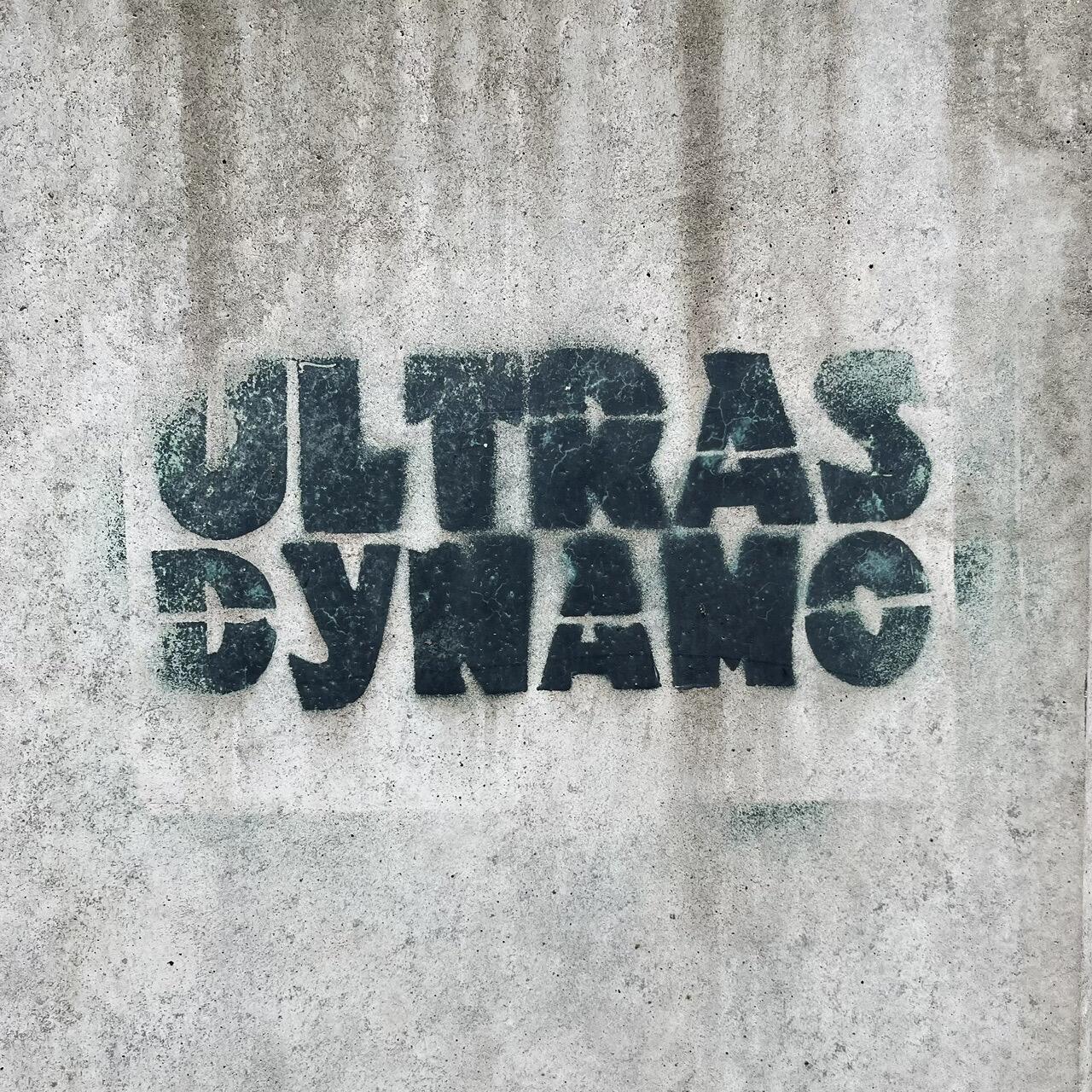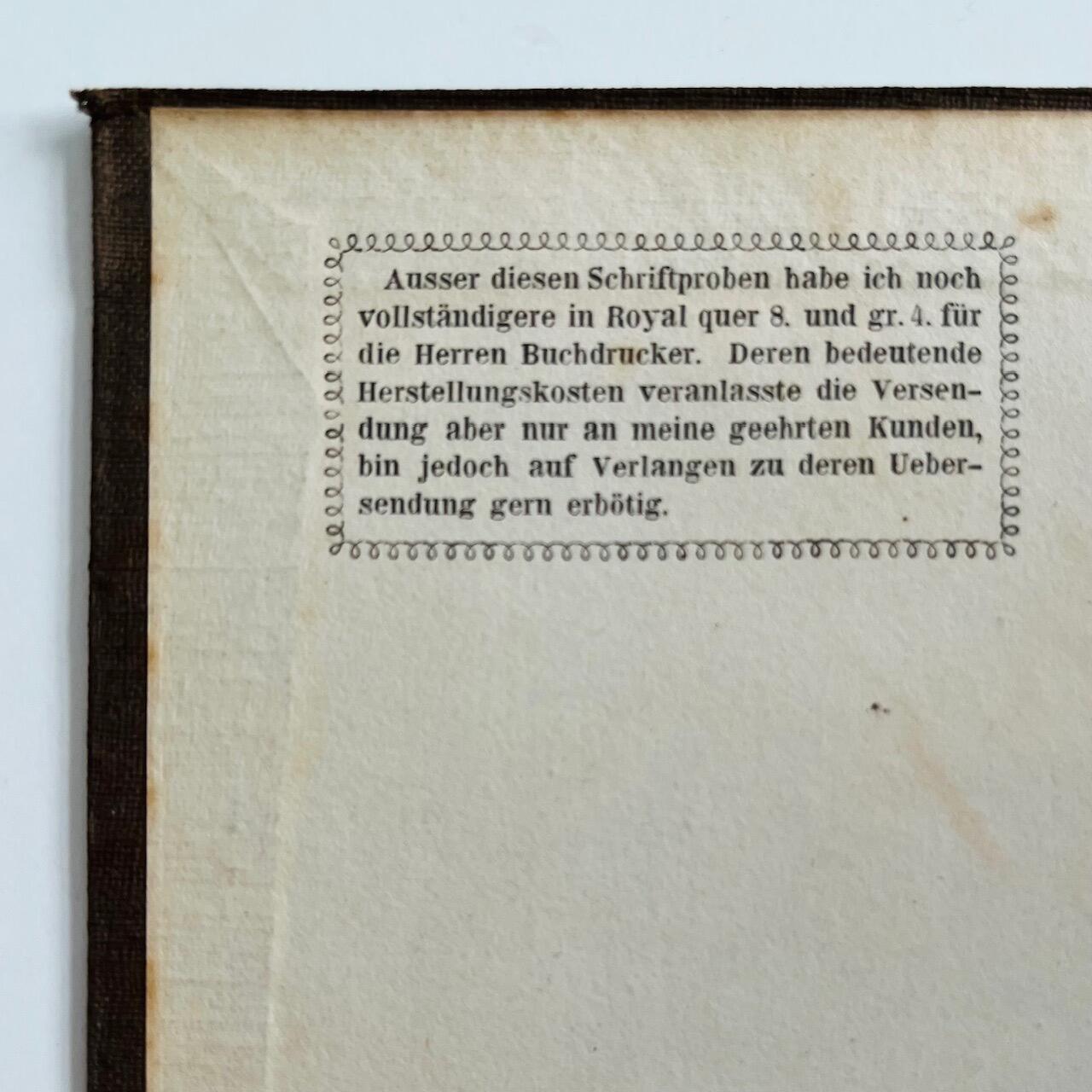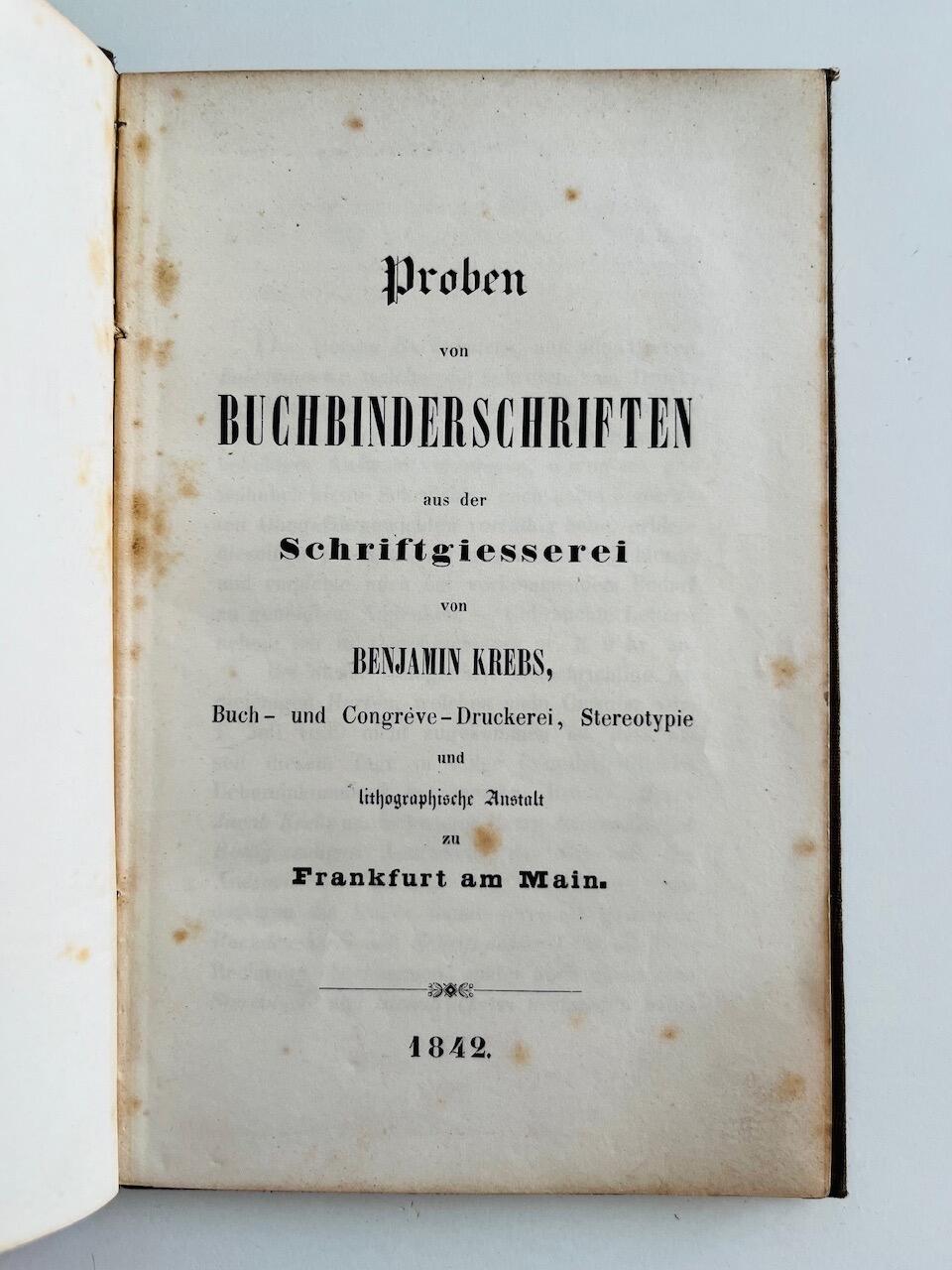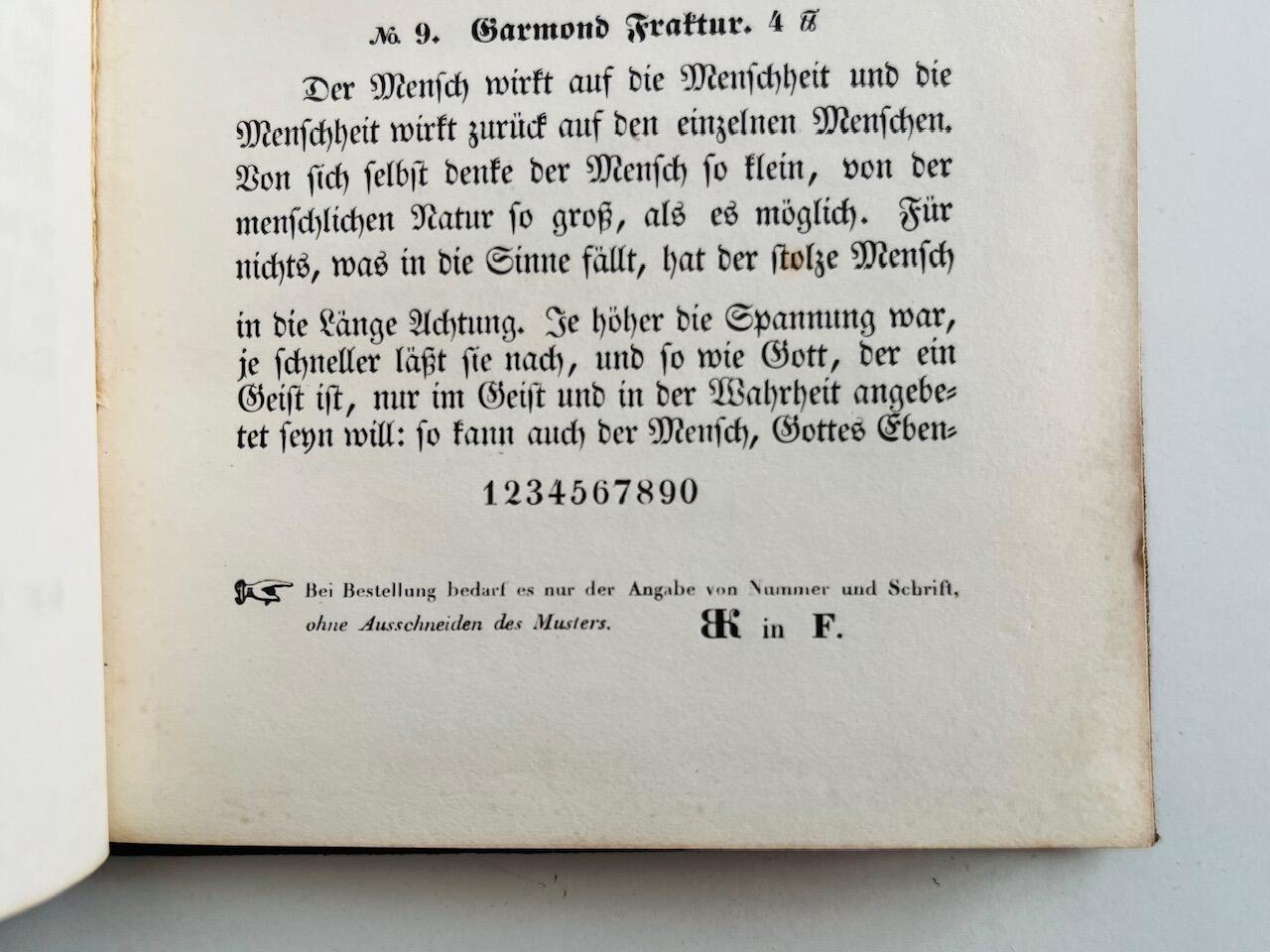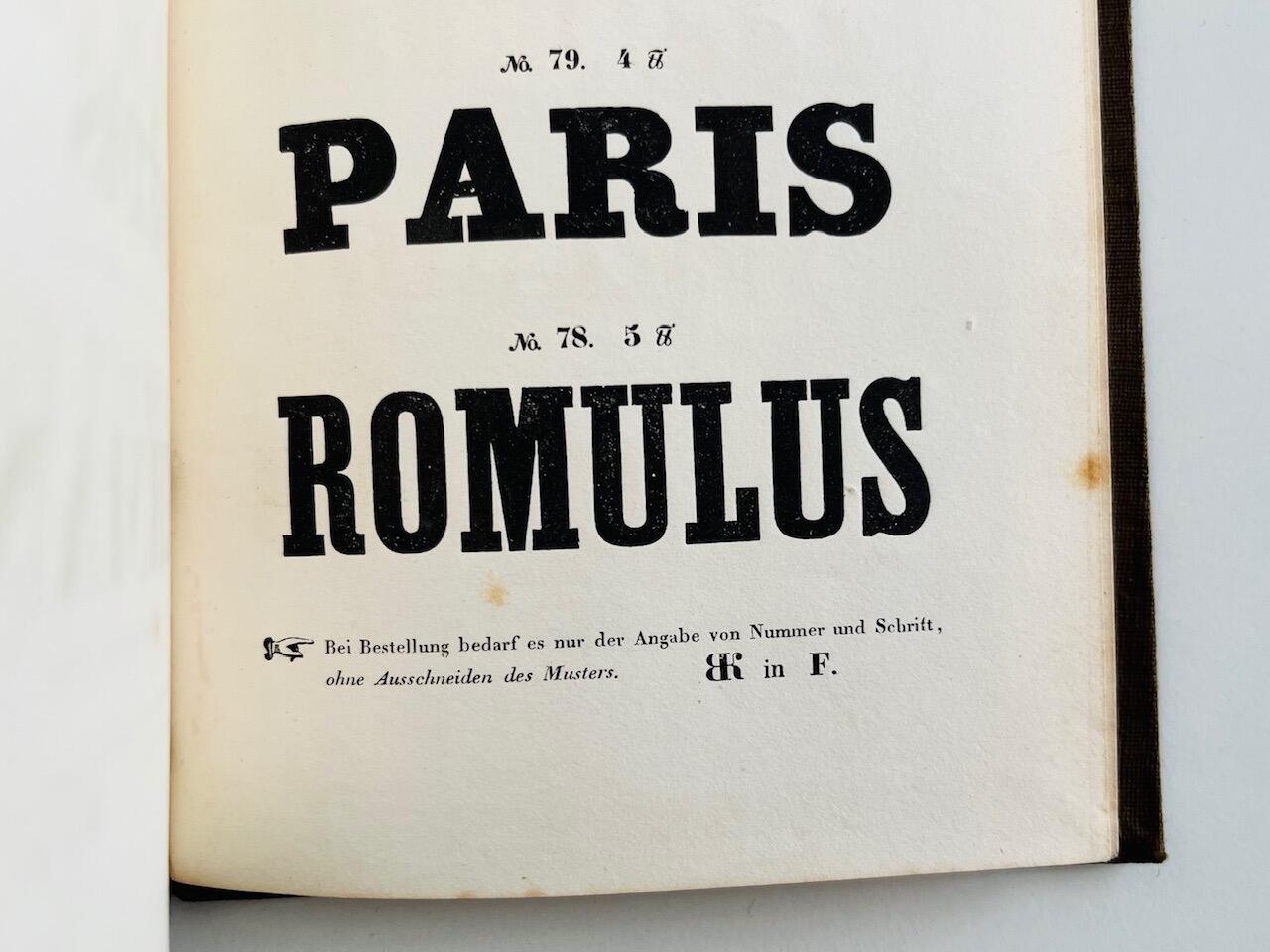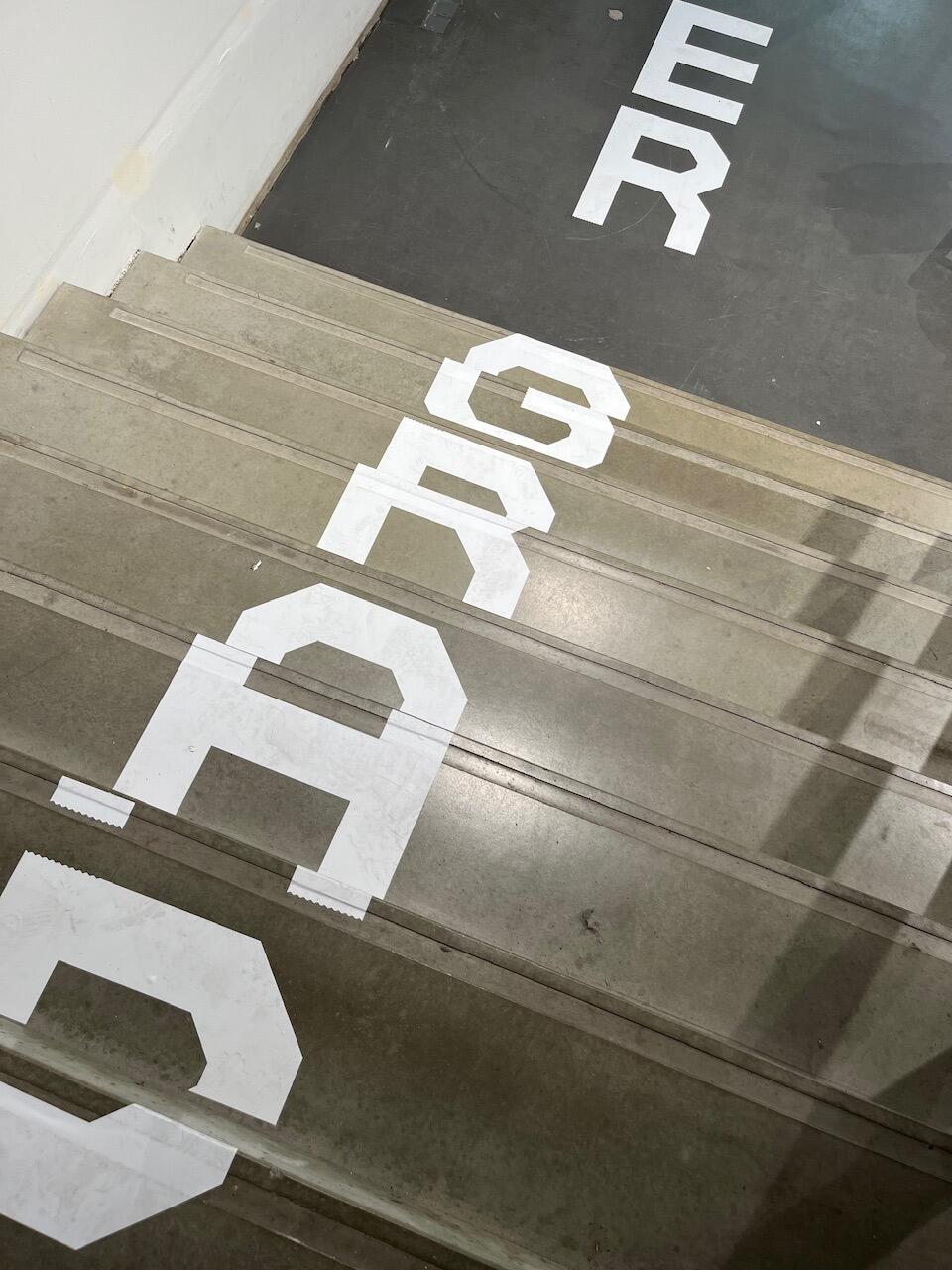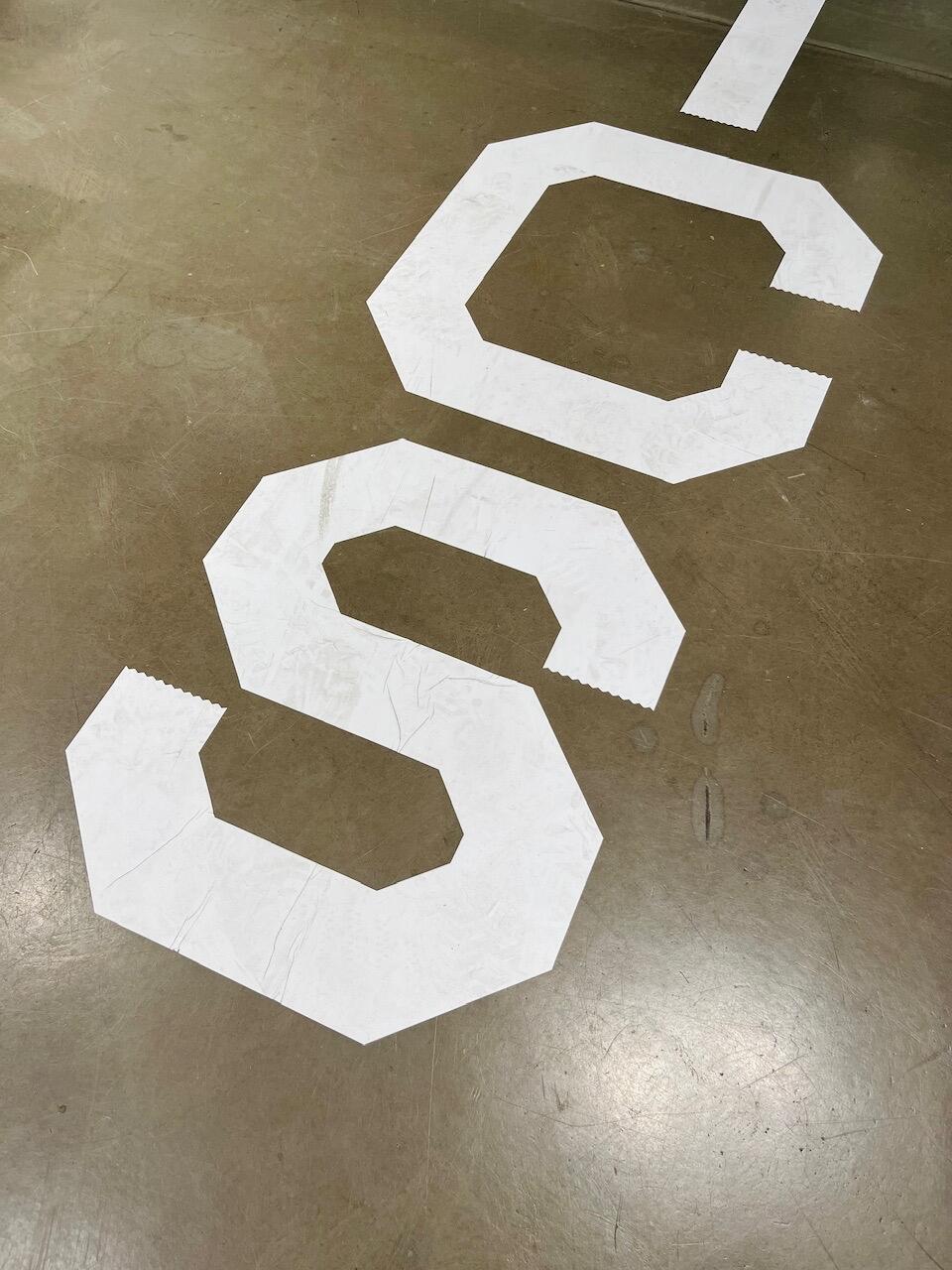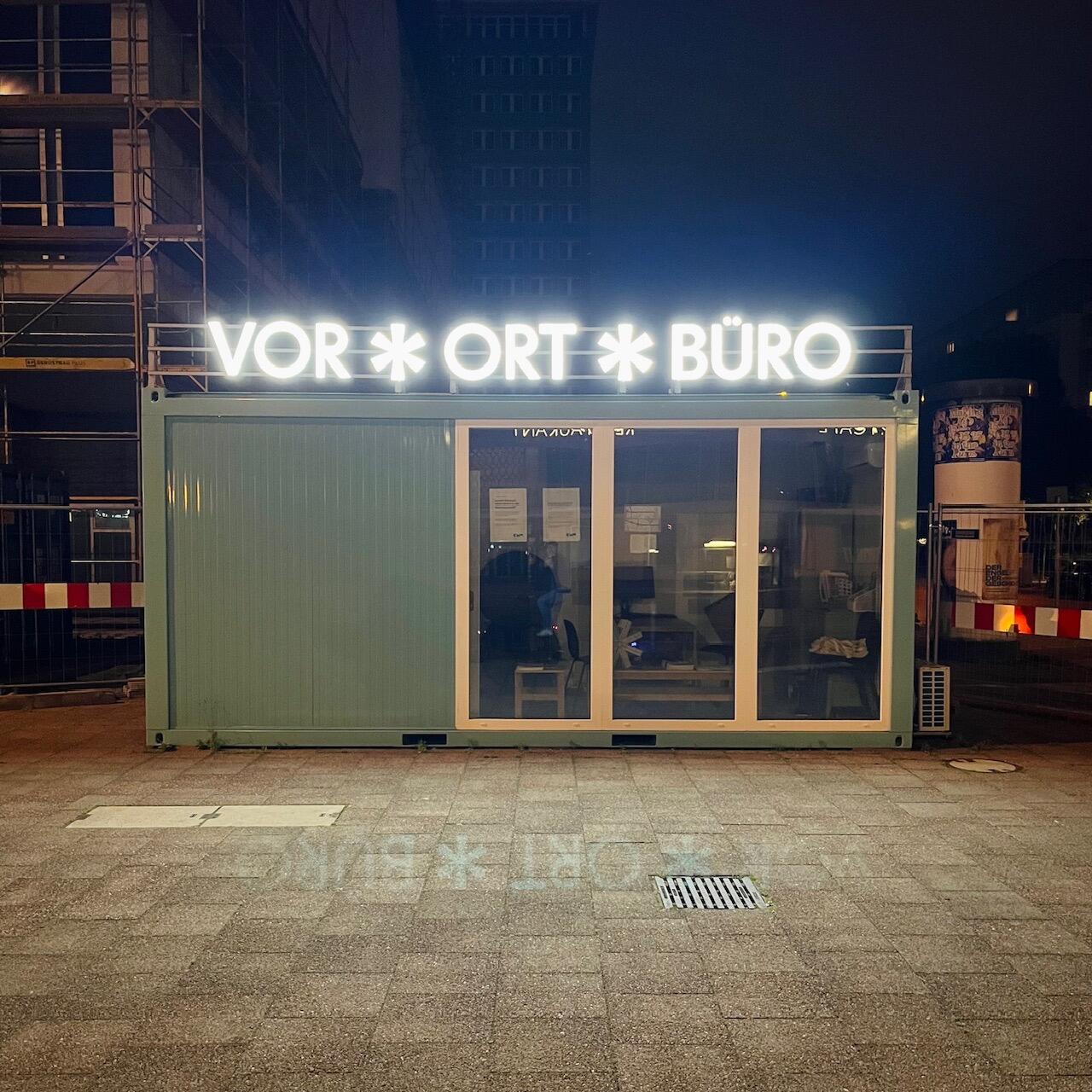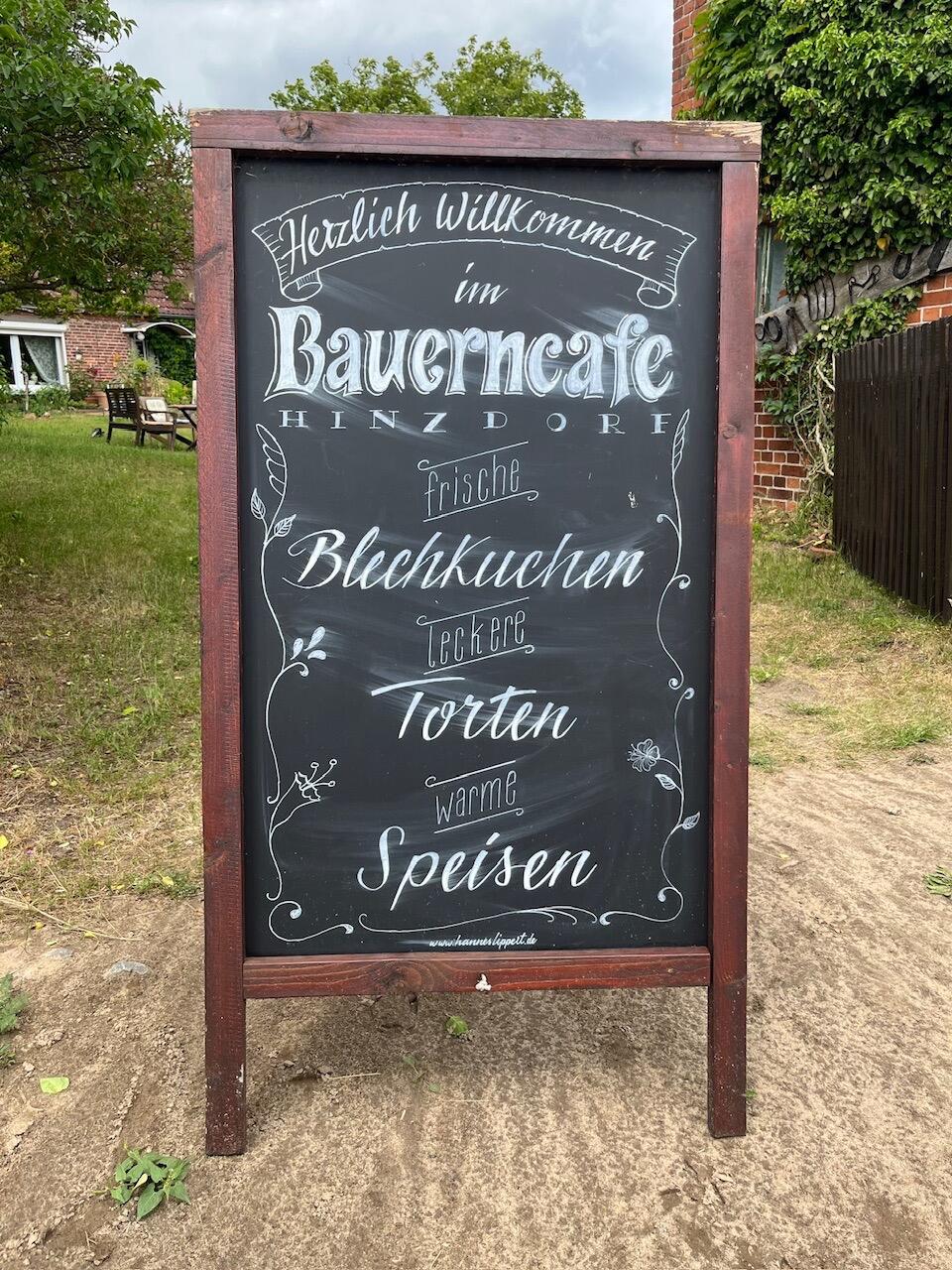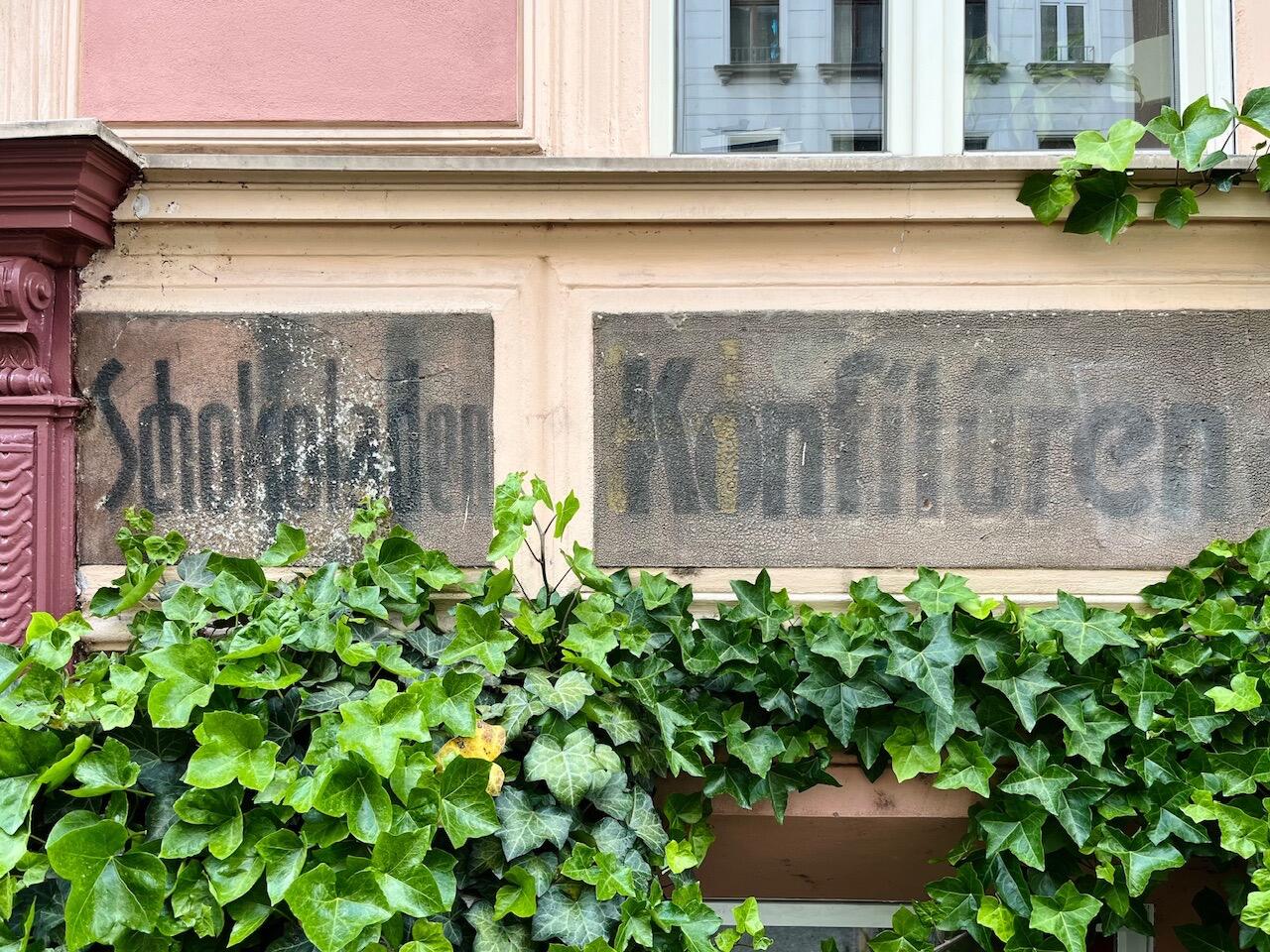
Formalästhetisch wegen des Minimalismus’ auch ganz interessant, finde ich …
PS: »Y bears the shortest place name in France, and one of the shortest in the world. The inhabitants call themselves Ypsilonien(ne)s, from the Greek letter Upsilon, which looks like the letter Y.«
Es gibt natürlich immer jemanden der eine Sache besser macht. Für mich zählt hier aber der Ansatz und im regionalen Kontext ist der für die Kunden quasi ein Quantensprung.
Und eine wohltuende Abwechslung zur Comic Sans. Ich find es ebenfalls toll, wenn sich jemand Mühe gibt. Und das W kann man ja noch mit einem kleinen Schwamm korrigieren … :-D
Mag ja nostalgisch- sentimentalen Charme haben, typografisch eher Papst Franziskus-Grab Niveau.
Ich finds insgesamt nicht schlecht, nur das Hinzdorf sieht etwas sehr improvisiert aus…
nachtrag zum grabdeckel des franziskus: in der selben kirche (sta. maria maggiore) liegt auch der erbauer derselben begraben, auch ein FRANCISCVS. der wurde 390 jahre früher begraben, aber bei seiner inschrift haben die steinmetze auch schon gepatzt. also: schlechtes kerning ist kein neuzeitliches phänomen.